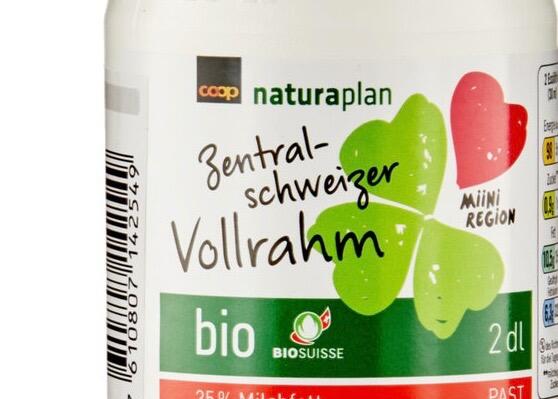
Suche Schrift in der «Zentralschweizer Vollrahm» gesetzt ist.
Habe beim Einkaufen im Schweizer Supermarkt «Coop» diesen Font entdeckt. Ich denke es ist eine Schriftart, da z.B das kleine «a» exakt gleich aussieht.
Eine Bildersuche nach »naturaplan ostschwijzer« findet noch jede Menge weitere Produkte. Ist also sicherlich eine Schrift.
Allerdings ist der Markt, speziell in dieser Creative-Market-Welt, voll mit Schriften in dieser Art. Wenn’s die automatischen Dienste nicht erkennen, wird die Suche etwas schwierig.